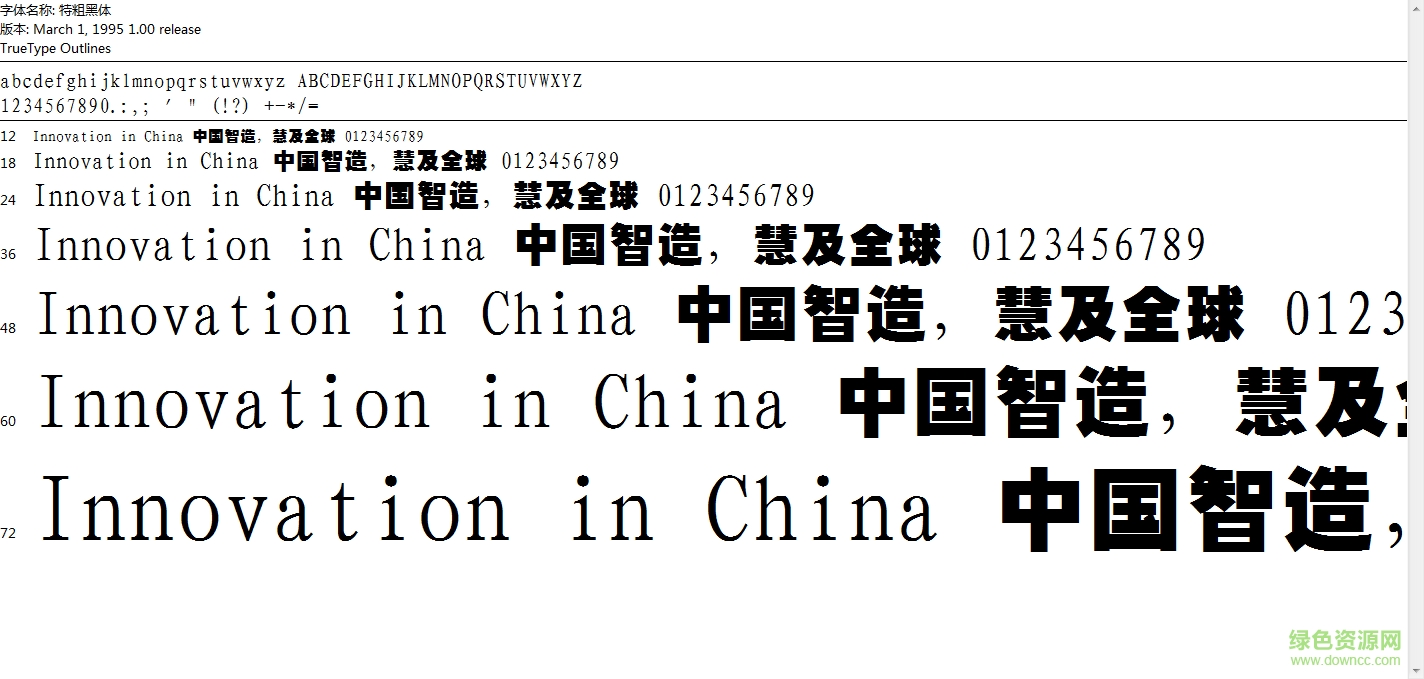
rstecuhei是什么字體? rs_tecuhei字體是一款四通利方特粗黑體,線條粗壯,外形突出,可用作文章、海報(bào)、ppt、報(bào)刊的大標(biāo)題,在生活中都是比較常見(jiàn)的,也能吸引大家的注目,需要的朋友可別錯(cuò)過(guò)了,歡迎登陸綠色資源網(wǎng)下載使用哦。